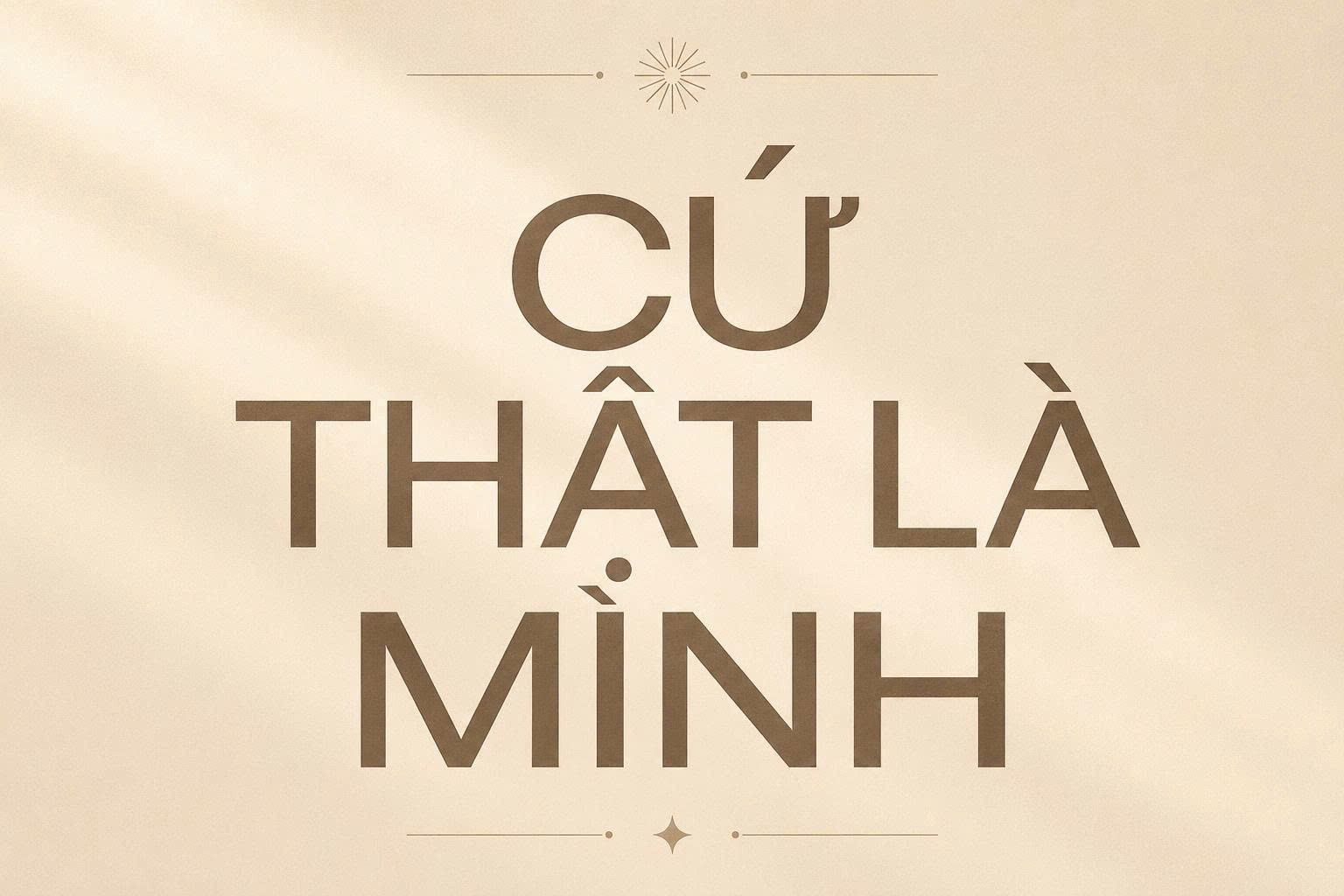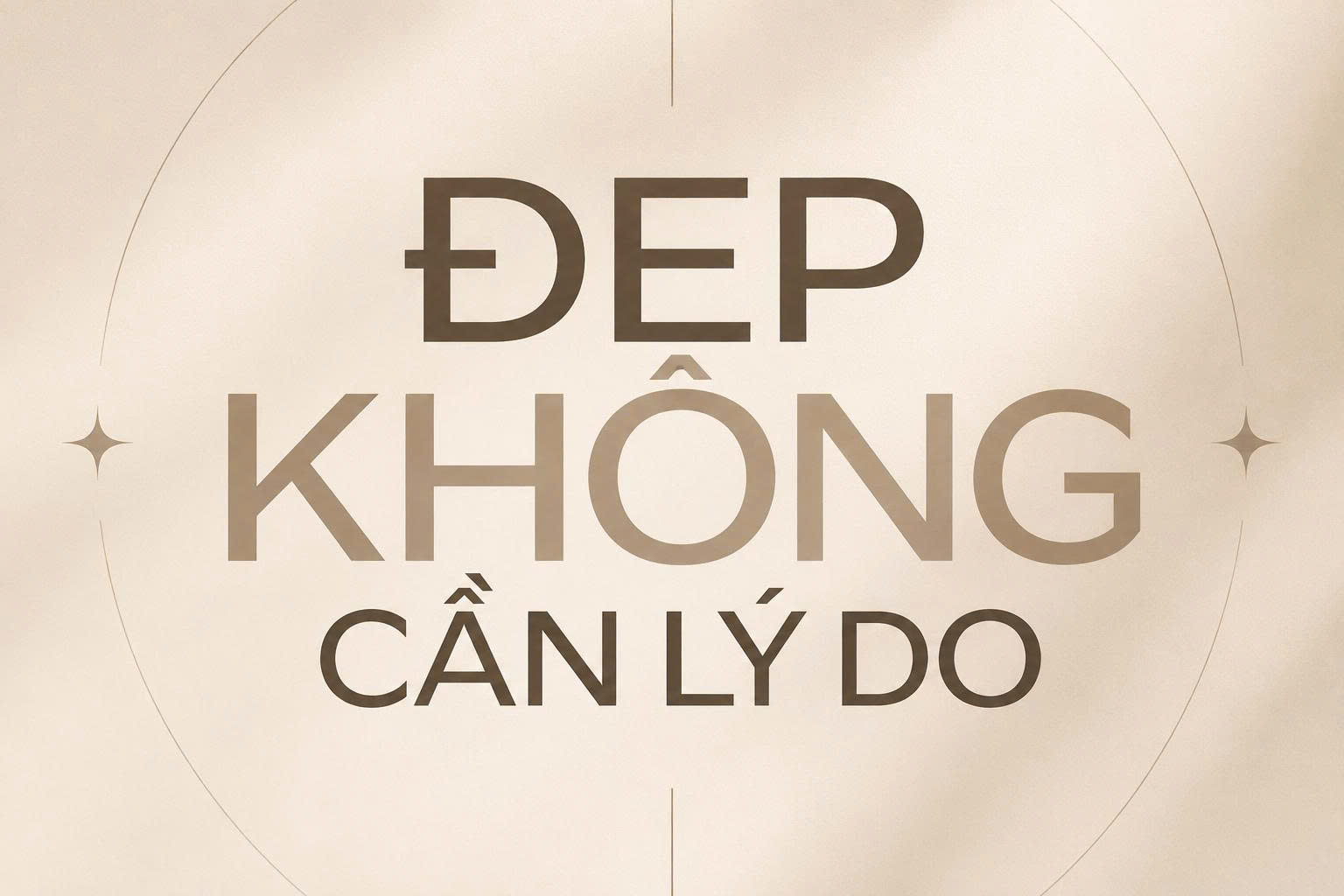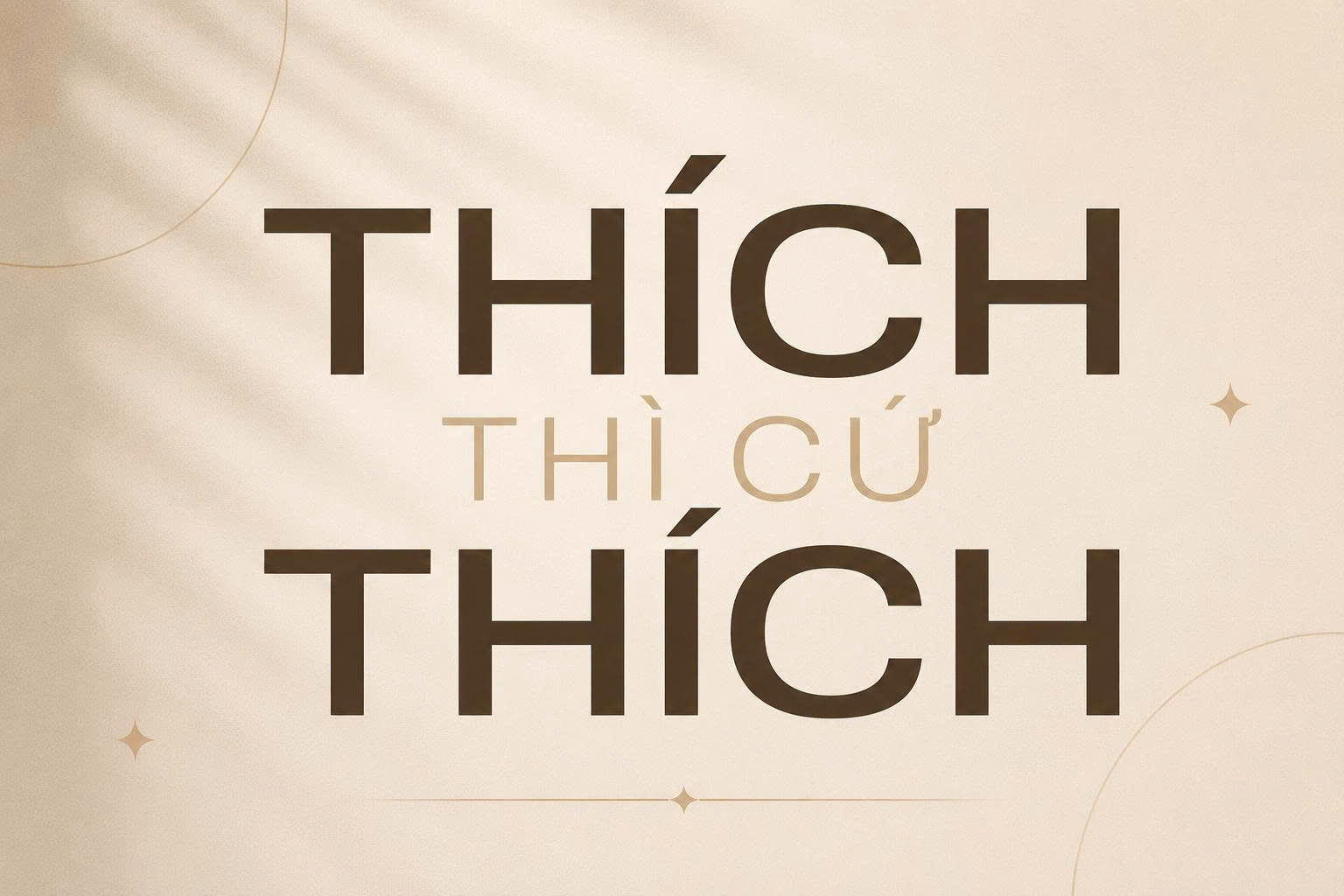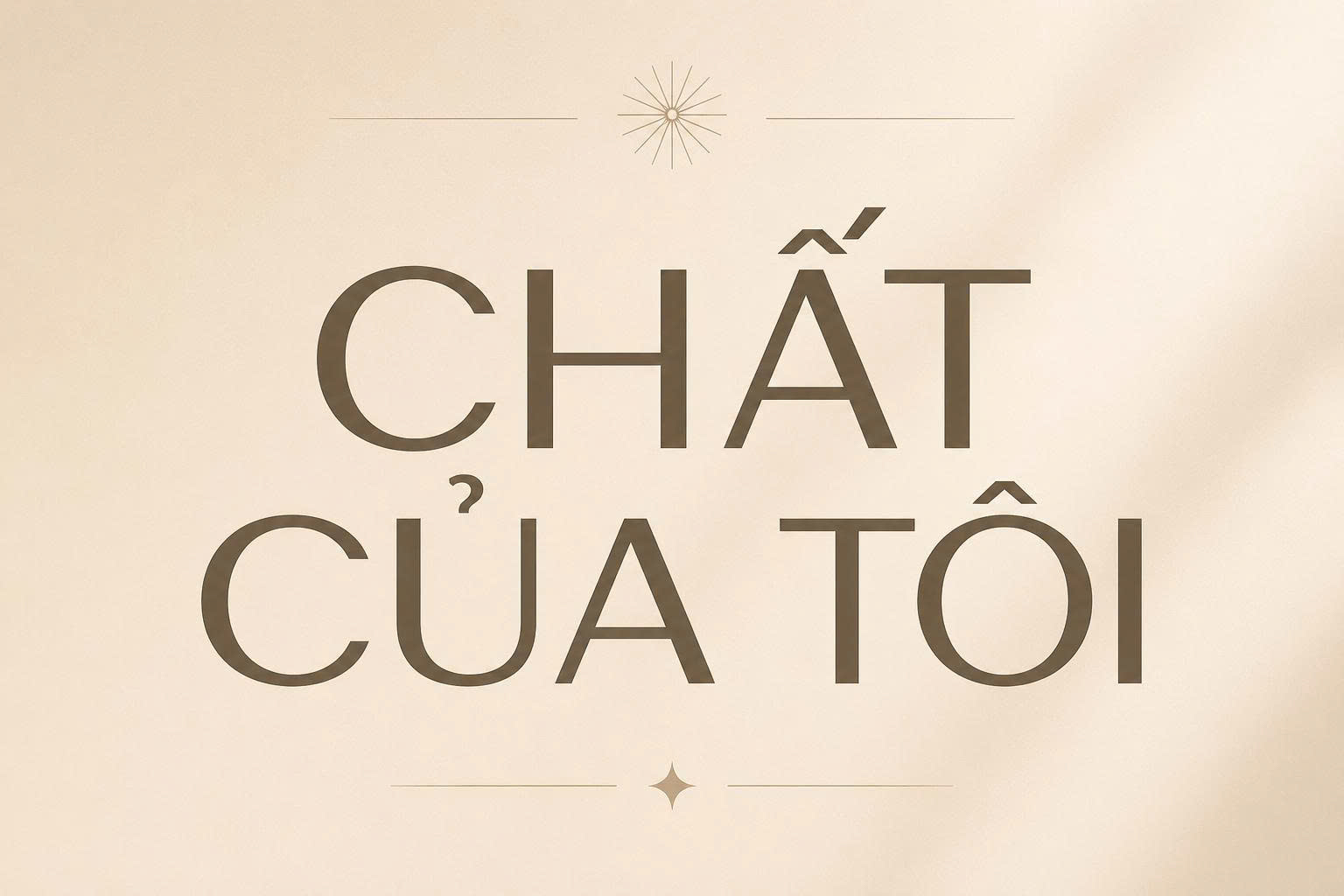
Font Việt hóa Cobe là bộ phông chữ thuộc dòng Sans-serif hiện đại với những đường nét tối giản, cấu trúc chữ rõ ràng và mang đậm hơi hướng hình học tinh tế. Được thiết kế nhằm tối ưu hóa khả năng hiển thị, Cobe mang lại cảm giác minh bạch, chuyên nghiệp và cực kỳ thời thượng cho các bản thiết kế thương hiệu. Doozypack.vn chia sẻ link tải trọn bộ phông chữ này với đầy đủ các biến thể, giúp bạn sở hữu bộ font chữ tiếng Việt Cobe Sans Serif hoàn hảo mà không lo gặp lỗi hiển thị dấu thanh.
Đặc điểm thiết kế của font chữ tiếng Việt Cobe Sans Serif
Cobe không chỉ đơn thuần là một bộ phông chữ không chân, nó là kết quả của việc nghiên cứu kỹ lưỡng về tỉ lệ và không gian chữ để tạo ra trải nghiệm đọc tốt nhất.
Cấu trúc chữ hình học cân đối và minh bạch
Đặc trưng lớn nhất của font Cobe chính là sự cân bằng tuyệt vời giữa các đường thẳng dứt khoát và các đường cong bo tròn mịn màng. Cấu trúc chữ mở rộng giúp các ký tự không bị dính vào nhau ngay cả khi trình bày ở mật độ dày. Đặc điểm này khiến Cobe trở thành lựa chọn lý tưởng cho các thiết kế giao diện website, ứng dụng di động và đặc biệt là các khối văn bản trên bao bì sản phẩm.
Độ dày nét đa dạng phục vụ mọi nhu cầu phân cấp thông tin
Hệ sinh thái font Cobe cung cấp nhiều cấp độ từ Thin (siêu mảnh) đến Black (cực đậm). Việc sở hữu đầy đủ các biến thể giúp designer dễ dàng thực hiện quy tắc phân cấp thị giác (Hierarchy), giúp người tiêu dùng nhanh chóng nhận diện được đâu là tên thương hiệu, đâu là thông tin mô tả sản phẩm trên cùng một mặt túi giấy hay hộp quà.
03 Lý do nên sử dụng font Cobe Việt hóa cho thiết kế thương hiệu?
- Dấu tiếng Việt được tinh chỉnh chỉn chu: Bản Việt hóa đảm bảo các bộ dấu được đặt đúng vị trí, không đè nét và giữ nguyên được tinh thần tối giản của font gốc.
- Tạo cảm giác chuyên nghiệp: Với vẻ ngoài hiện đại, Cobe giúp thương hiệu toát lên sự uy tín, minh bạch, rất phù hợp với ngành mỹ phẩm, dược phẩm và công nghệ.
- Khả năng phối hợp linh hoạt: Bạn có thể dễ dàng kết hợp Cobe với một font có chân (Serif) truyền thống hoặc một font viết tay (Script) để tạo sự tương phản đầy tính nghệ thuật.
| Biến thể Font | Đặc điểm thị giác | Ứng dụng đề xuất tại Doozypack.vn |
| Cobe Light/ExtraLight | Thanh mảnh, tinh tế | Dùng cho ghi chú nhỏ, địa chỉ hoặc mã vạch trên vỏ hộp. |
| Cobe Regular/Medium | Dễ đọc, tiêu chuẩn | Dùng cho bảng thành phần, hướng dẫn sử dụng sản phẩm. |
| Cobe Bold/Black | Mạnh mẽ, vững chãi | Dùng làm tiêu đề chính, slogan hoặc tên sản phẩm trên túi giấy. |